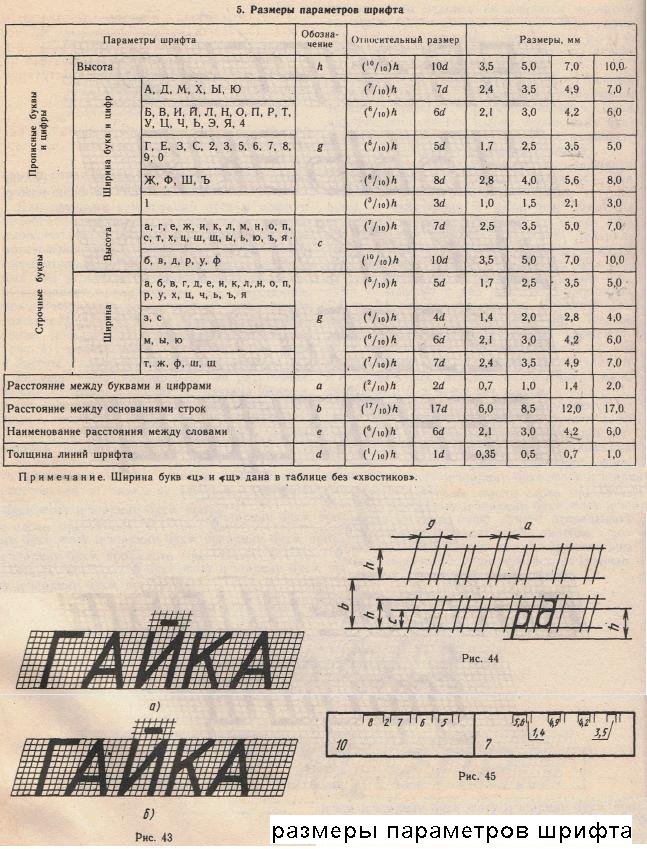
Чертежный шрифт
Практическая работа №4 Шрифтом называется однородное начертание всех букв алфавита и цифр, которое придает им общий характерный облик. Чертежный шрифт должен легко читаться и быть простым в написании. На чертежах и других конструкторских документах всех отраслей промышленности и строительства применяют чертежный шрифт, который устанавливает ГОСТ 2.304 - 81 (СТ СЭВ 851 – 78-СТ СЭВ 855-78). ГОСТ устанавливает следующие размеры шрифта: (1,8); 2,5; 3,5; 5; 7; 10; 14; 20; 28; 40. Применение шрифта размером 1,8 не рекомендуется и допускается только для шрифта типа Б. Размер шрифта определяется высотой прописных букв в миллиметрах. Высота букв h измеряется перпендикулярно к основанию строки.ГОСТом установлены следующие типы шрифта: тип А с наклоном около 75°; тип А без наклона. В учебных заведениях обычно пользуются шрифтом типа Б с наклоном 75° Для изучения конструкции букв и цифр и приобретения навыков их написания следует выполнить несколько надписей с помощью вспомогательной сетки. Сетка состоит из тонких горизонтальных и наклонных линий, проведенных под углом 75° к горизонтальной линии, и выполняется карандашом 2Т. Расстояние между параллельными линиями сетки равно толщине линий шрифта с выбранного для написания (рис. 40). Толщина линий шрифта d (рис. 41) определяется в зависимости от типа и высоты шрифта h (размера шрифта). Размеры таких параметров, как расстояние между буквами в словах а, ширина букв и цифр g, минимальное расстояние между словами е, расстояние между основаниями строк, для наиболее применяемых размеров шрифта типа Б следует брать из таблицы. Если в предложении есть знаки препинания, то расстояние между словами определяется расстоянием от знака препинания до первой буквы следующего слова. Если надпись начинается с прописной буквы, а остальные буквы строчные, то высота строчных букв, кроме букв б, в, д, р, у, ф равна предыдущему размеру шрифта. Например, если надпись выполняется шрифтом размером 10, то высота строчных букв равна 7 мм. Высота строчных букв б, в, д, р, у, ф равна высоте прописных букв размера шрифта, которым выполняется надпись. Толщина обводки прописных и строчных букв в одном слове должна быть одинаковой согласно принятому размеру шрифта. Если надпись выполняется только прописными буквами, то первая буква по высоте не выделяется; все буквы имеют одинаковую высоту. Конструкции цифр и букв русского алфавита для шрифта типа Б показаны на рисунке ниже. Для наглядности прямолинейные участки затушеваны, а скругления и наклонные элементы оставлены светлыми. Промежутки между двумя смежными буквами, имеющими непараллельные пограничные линии, зрительно кажутся увеличенными, поэтому в сочетаниях букв Л, ГЛ, АД, АЛ, КА, ГЦ промежуток между буквами уменьшают в два раза, а в сочетаниях ГА и ТА не делают совсем. Сравните два написания одного слова (рис. 43). Первое слово выполнено с одинаковыми промежутками между всеми буквами (рис. 43, а). Во втором слове (рис. 43, б) между буквами К и А промежуток уменьшен наполовину, а между буквами Г и А его нет совсем. Все надписи на чертежах выполняются от руки. При изучении конструкции букв и цифр необходимо пользоваться вспомогательной сеткой, показанной на рисунке 40, овладев навыками написания шрифта, следует применять упрощенную вспомогательную сетку (рисунок 44), которая ограничивает высоту и ширину букв, промежутки между буквами и словами. Размеры элементов букв и цифр лучше откладывать по самодельной разметочной линейке, сделанной из бумаги, так как из-за толщины обычной линейки размеры переносятся неточно.